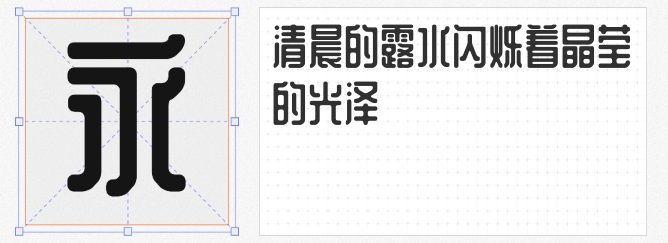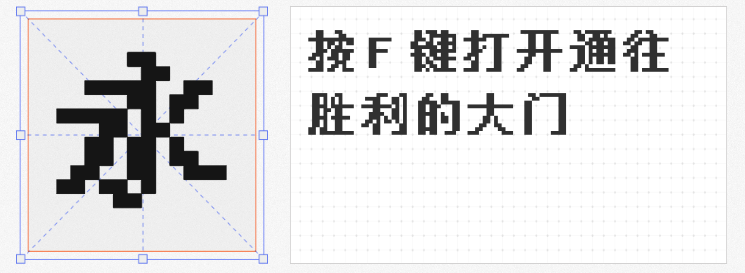
在商业设计领域,字体不仅是信息载体,更是品牌视觉语言的核心符号。本文精选四款风格迥异且可免费商用的创意字体,从像素艺术到几何美学,从繁体适配到法式浪漫,为设计师提供突破常规的字体解决方案。
作为基于文泉驿点阵中文字库开发的粗体点阵字体,天王星像素以6763个GB/T 2312-80标准汉字构建出独特的数字美学。其核心优势在于通过精确的像素间距控制,彻底消除传统点阵字体的笔画粘连问题,在8-12pt小字号场景下仍能保持清晰锐利的显示效果。该字体特别适用于科技产品界面、像素风游戏UI及复古海报设计,其方块状笔画与现代极简主义形成强烈反差,为数字原住民品牌提供精准的视觉锚点。
这款字体,通过"黑与白"的二元对立构建出极具冲击力的视觉系统。设计师将转折处全部直角化处理,撇捺转化为直线,却在点元素中注入圆形元素,形成方圆交融的矛盾美学。在品牌VI设计中,其超粗字重可单独作为图形符号使用,而细字重则适合长文本排版。
针对站酷庆科黄油体的功能缺失,马来西亚设计师夜煞之乐开发的滑油字SC版完成三大突破:新增繁体中文支持、补全标点符号体系、修正23处字形错误。该字体特别优化了"辶""阝"等复杂部首的显示效果,在港台地区品牌进军大陆市场时,可无缝切换简繁体而不破坏视觉统一性。
这款收录7608个字符的开源字体,通过"曲线折角+规律加粗"的设计语言,创造出类似法棍面包的纤细质感。其笔画末端特有的微弧处理,既保留了黑体的现代感,又融入手写体的温度。
在AI生成内容泛滥的当下,这四款字体以独特的设计哲学证明:人工设计的温度与机器效率并非对立关系。当品牌需要传递复古情怀、科技锋芒、文化包容或生活美学时,这些经过时间淬炼的创意字体,正在重新定义商业设计的价值边界。